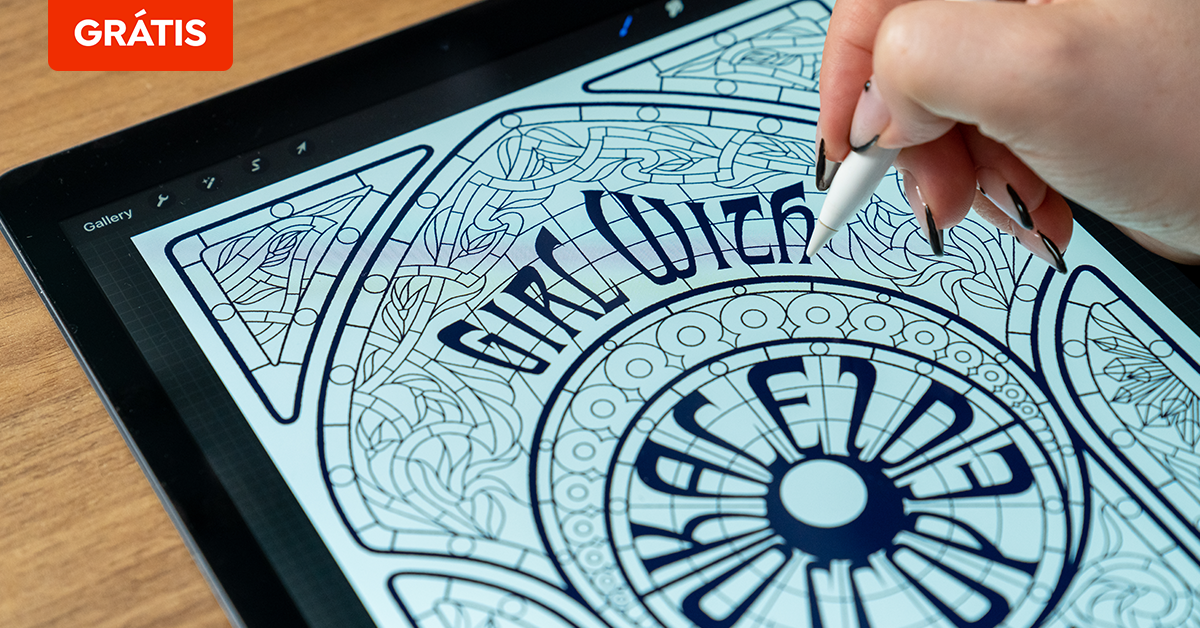
Uma composição de lettering ilustrado é capaz de desconstruir as formas como as conhecemos, entregando como resultado uma poesia visual. Para isso, dominar os conceitos básicos de caligrafia e tipografia é essencial.
Mas, antes de baixar o arquivo, aprenda no tutorial abaixo como criar, passo a passo, uma letra estilizada e aplicá-la em tela com recursos simples.
Tutorial Lettering: como criar uma letra autoral em tela
No encontro entre a tipografia e a caligrafia, o hand lettering reúne letras, cores e texturas para dar às palavras tonalidades visuais únicas e inspiradoras. Estes são os princípios que norteiam o trabalho de Lygia Pires.
Neste tutorial, Lygia ensina como criar uma letra estilizada e aplicá-la em tela utilizando recursos simples como papel e marcador.